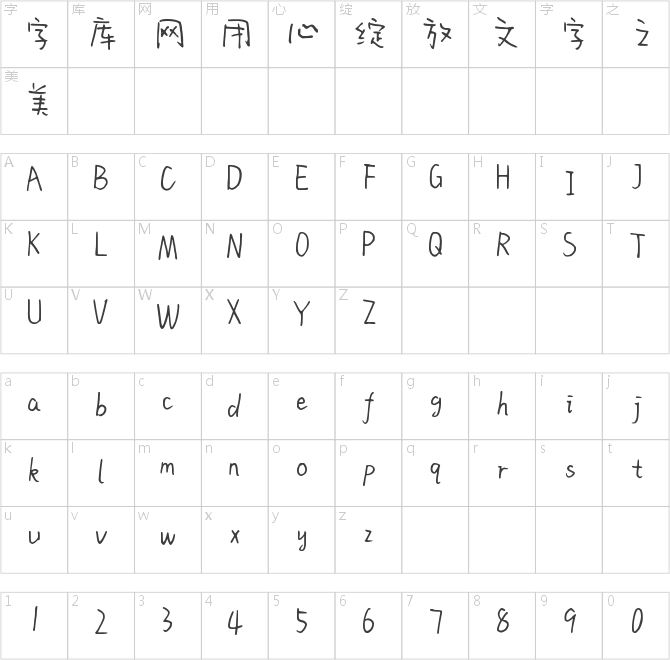
字語(yǔ)坊
松果體這款字是一款風(fēng)格可愛(ài)的手寫(xiě)體,字體筆畫(huà)簡(jiǎn)單直接,該字跳動(dòng)的旋律感,及搖曳生姿的字形,童趣可愛(ài),自在隨性,由內(nèi)而外的歡喜。適用于文藝類(lèi)的書(shū)刊、少年兒童類(lèi)的書(shū)刊、品牌廣告和產(chǎn)品包裝設(shè)計(jì)等。